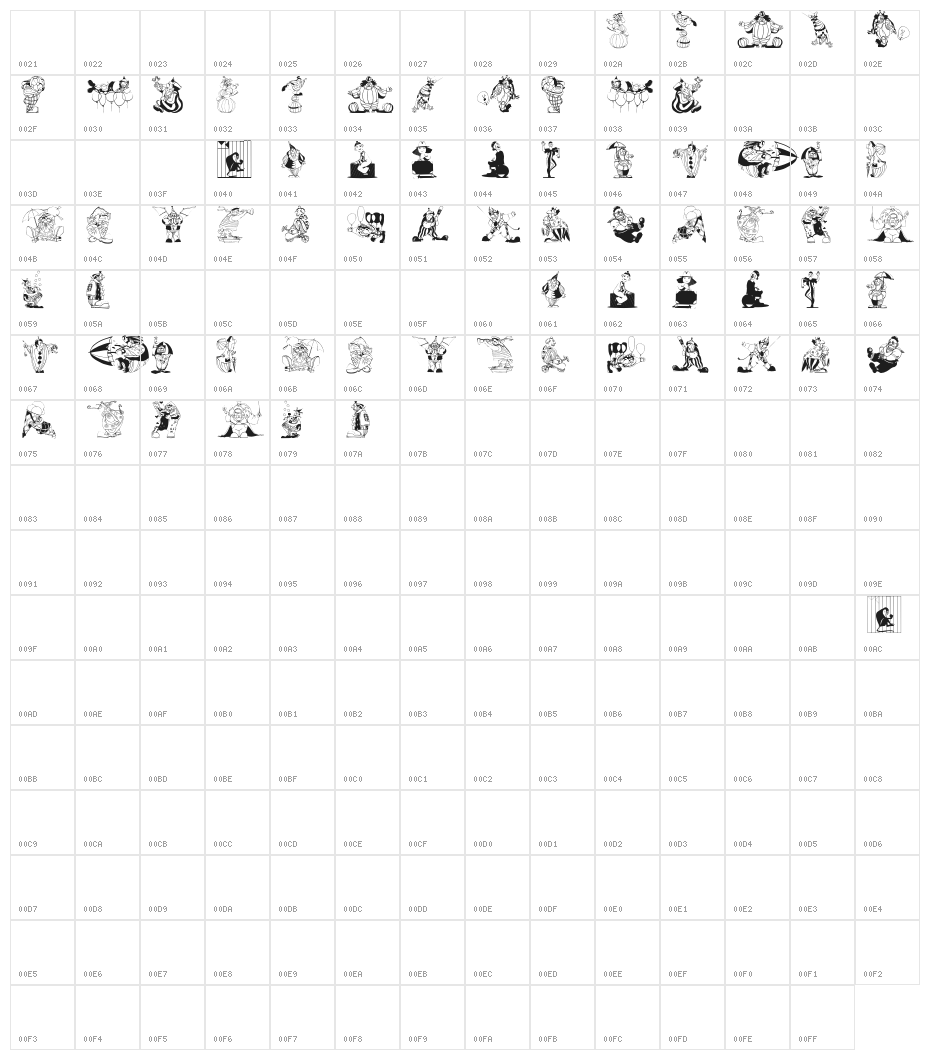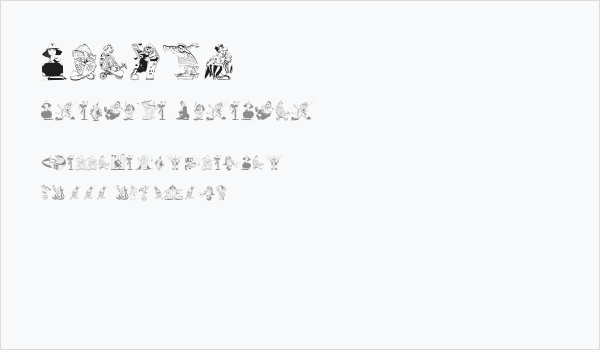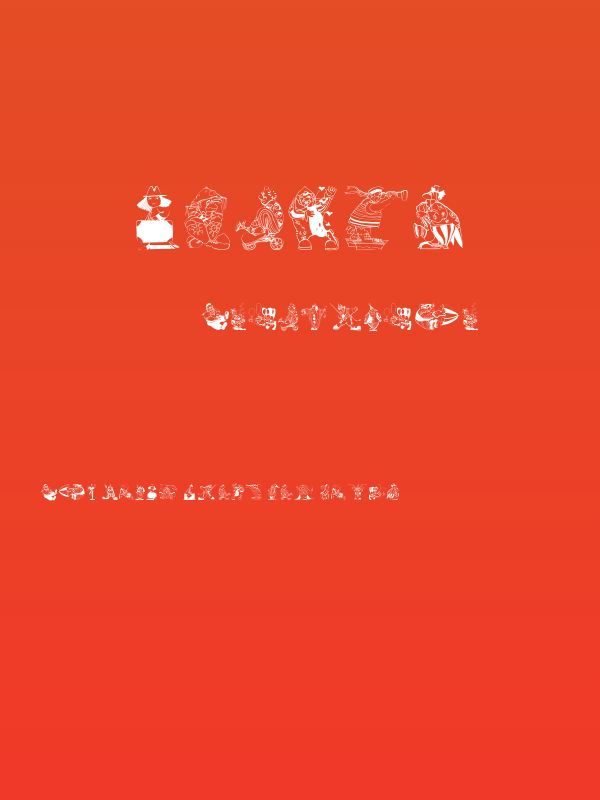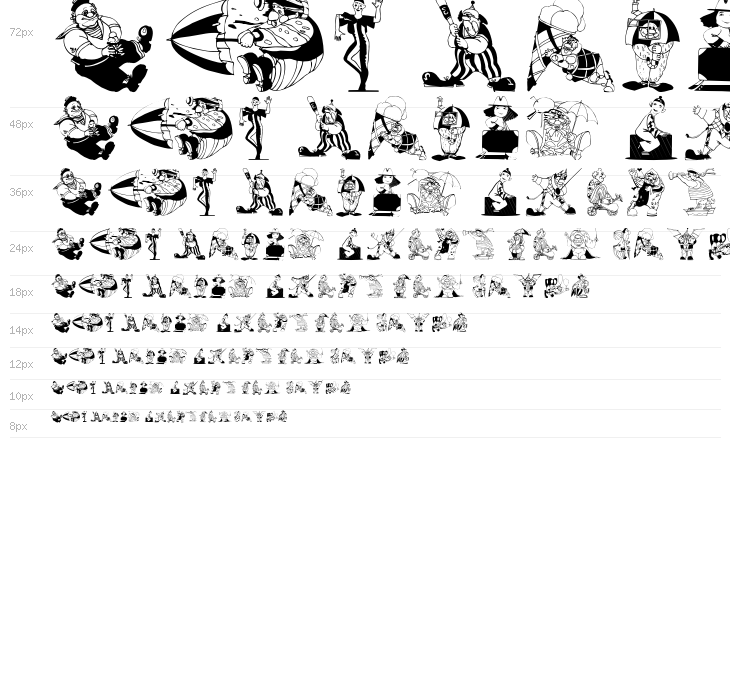
Clowns Font
| Stile generale | Decorative, Whimsical, Playful |
| Caso d'uso | Logos, Headlines, Posters, Themed Events |
| Progetti proposti | Children’s party invitations, circus-themed posters, playful branding, event flyers, novelty merchandise. |